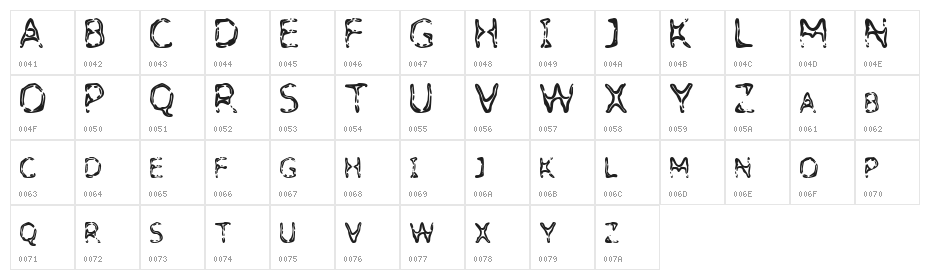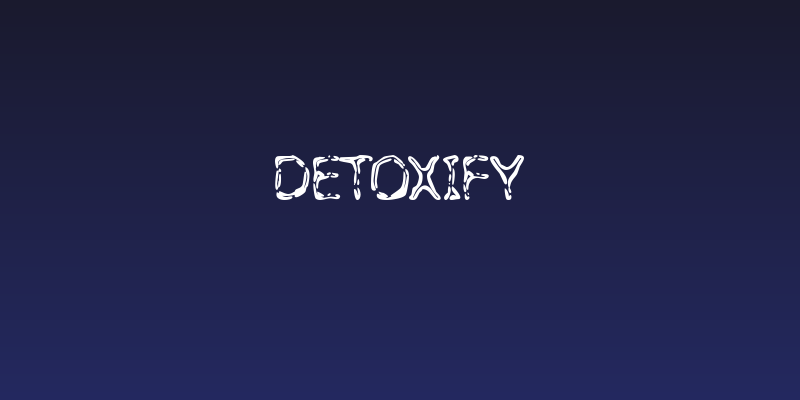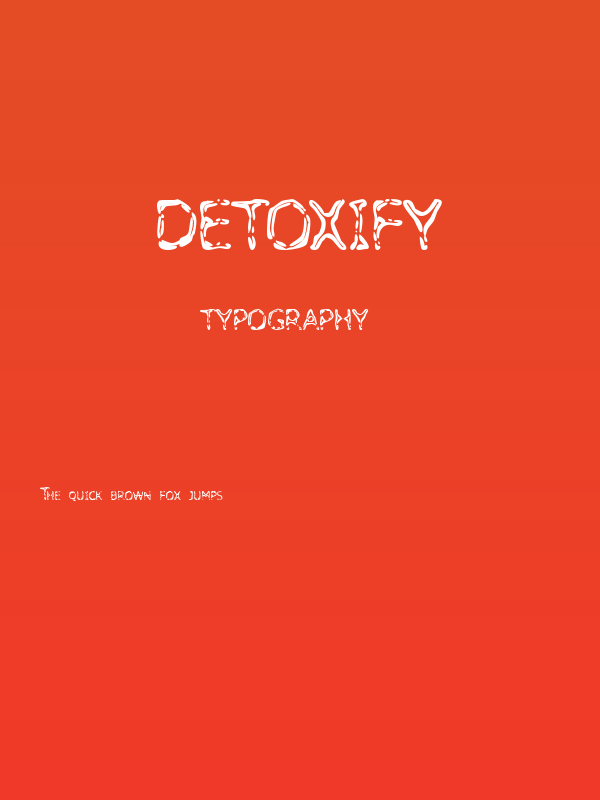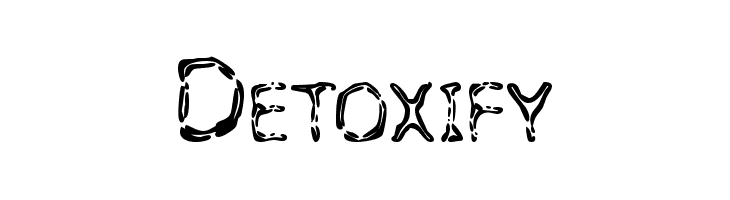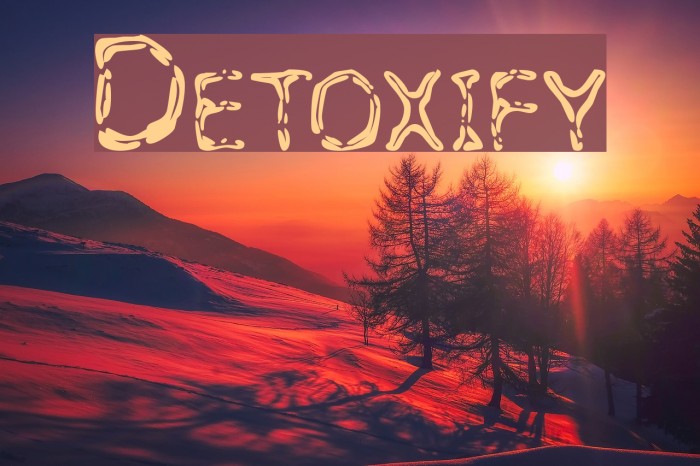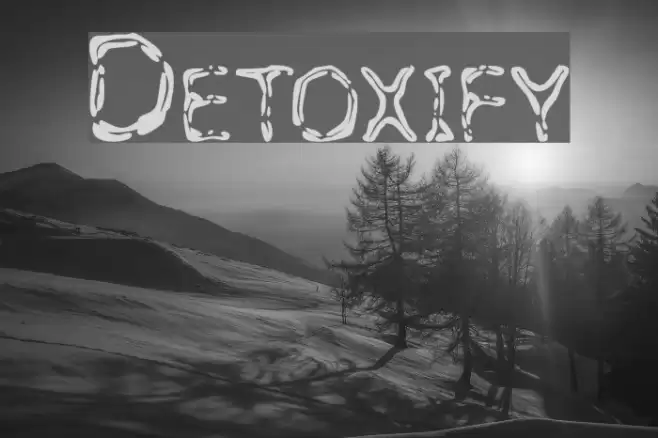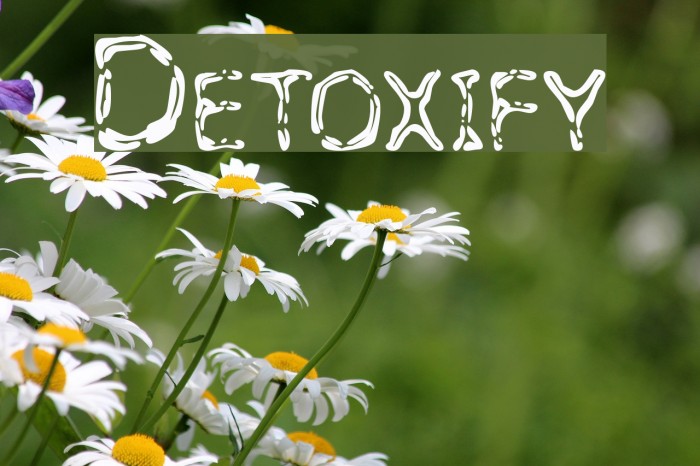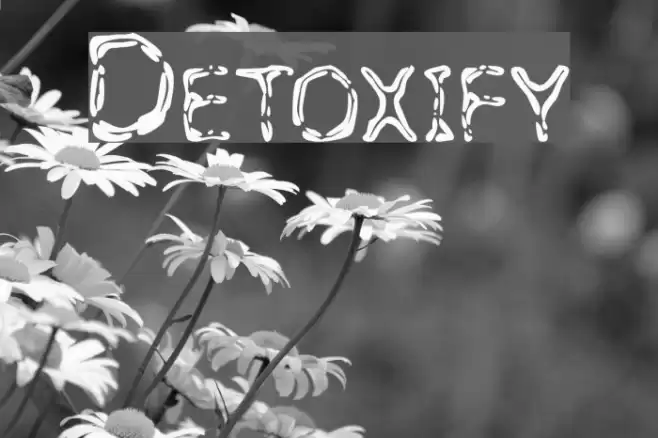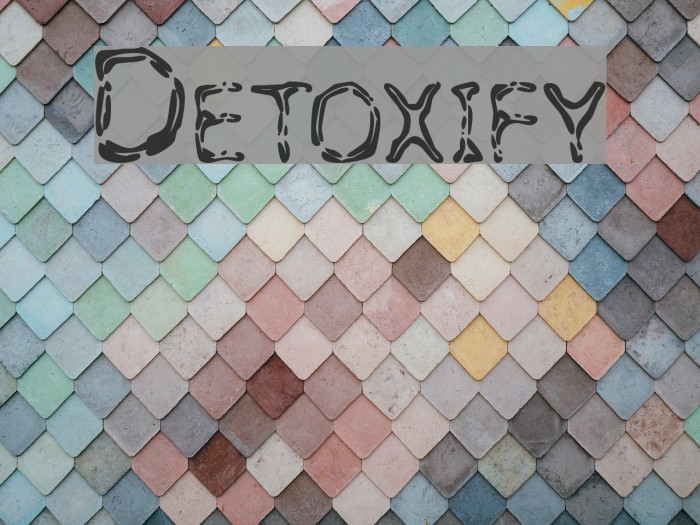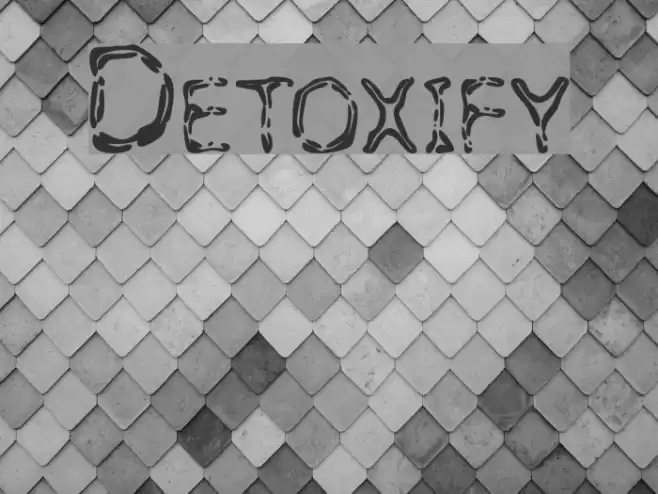
Detoxify Font
| Style général | Modern, Decorative |
| Projets proposés | Ideal for creative projects such as posters, album covers, branding for artistic events, or any design requiring a bold, eye-catching typeface. |